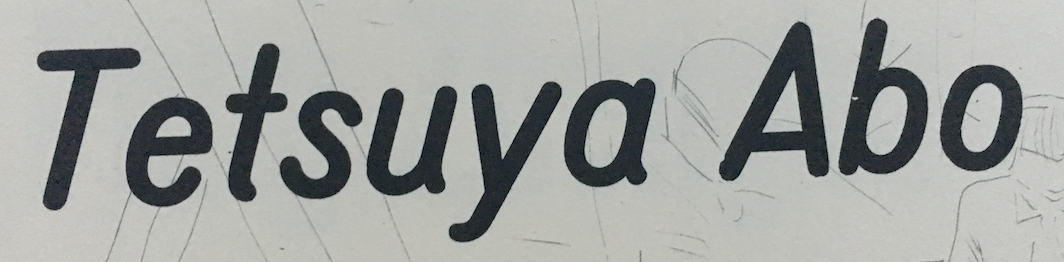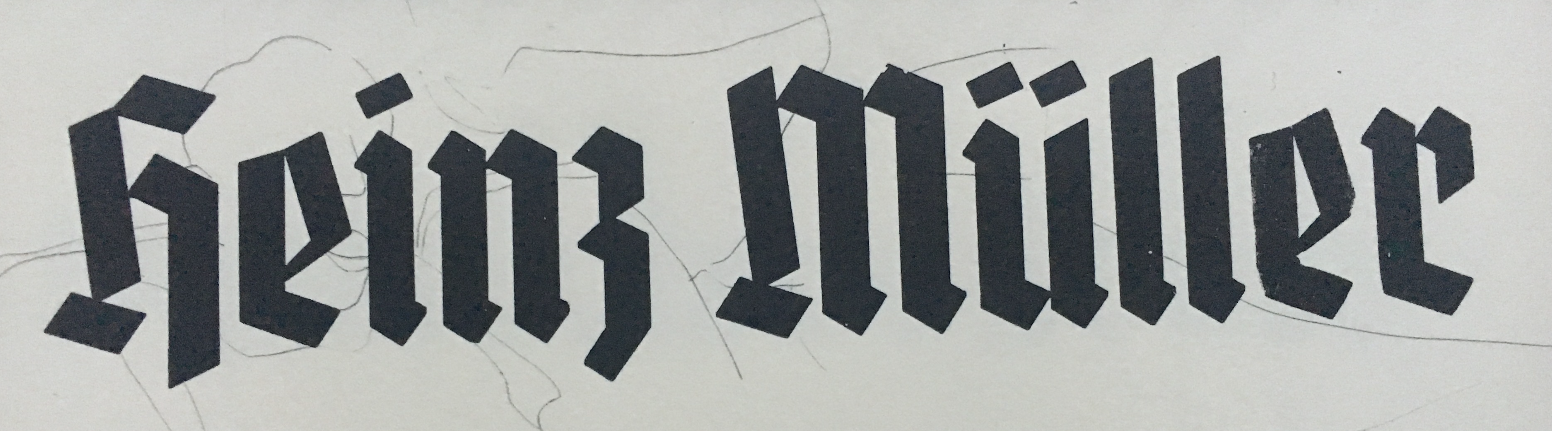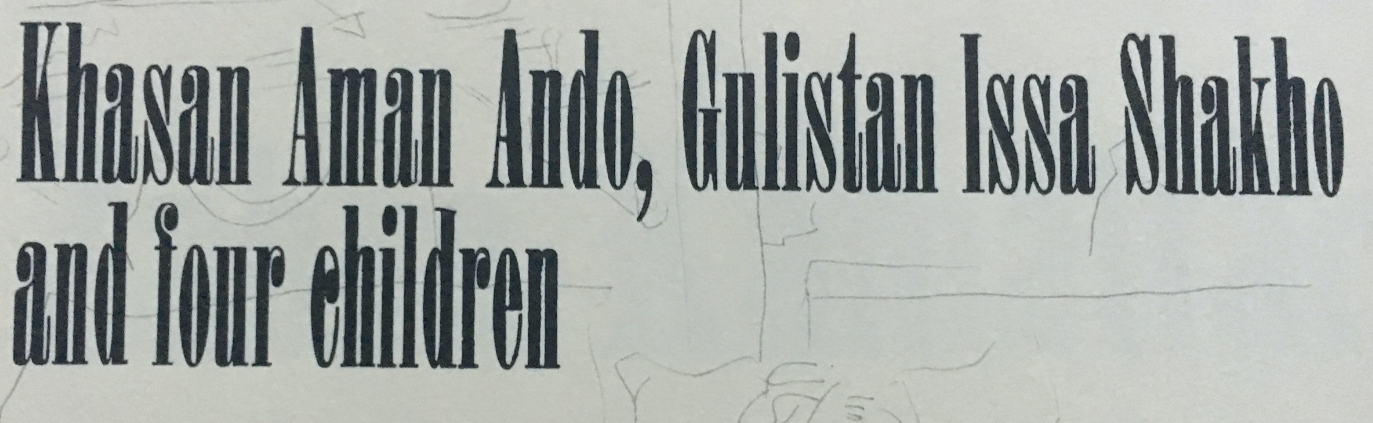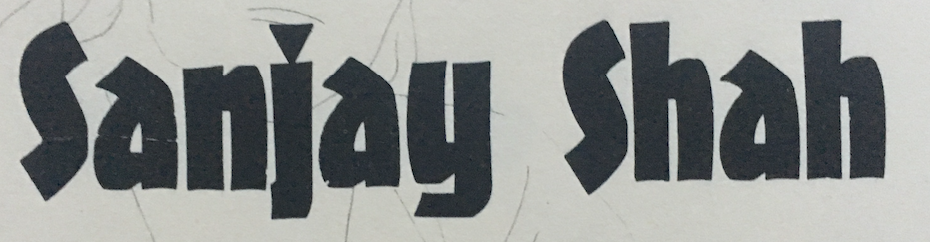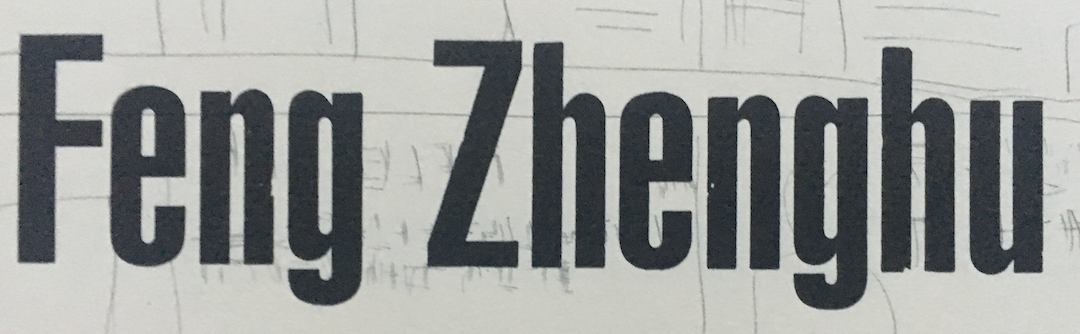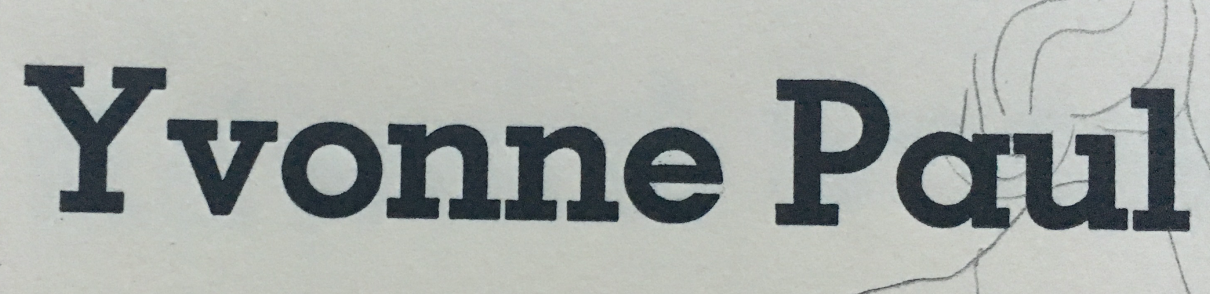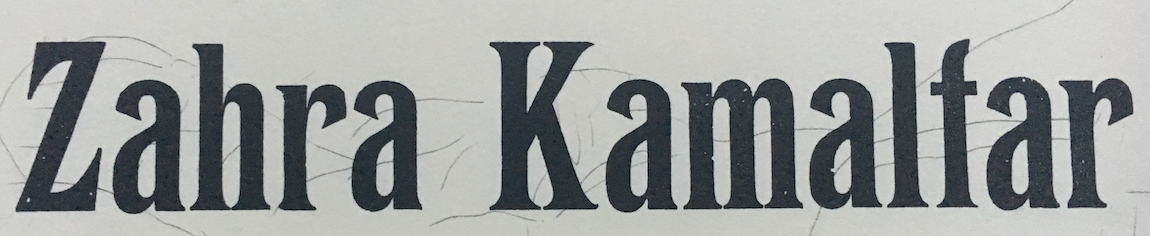
Suche Hilfe bei Identifizierung von Bleisatz-Schriften aus Hersbrucker Bücherwerkstätte
ich habe letzte Woche in der Hersbrucker Bücherwerkstätte http://www.hersbrucker-buecherwerkstaette.de/ ein kleines Heft gedruckt, und nun bin ich dabei die von mir verwendeten Schriften zu recherchieren. Es gibt die Hersbrucker Bücherwerkstatt seit fast 50 Jahren und die Betreiber – gelernte Drucker – haben einige Schriften vor dem Müll gerettet. Die Schrift-Schubladen sind  allerdings sind nicht beschriftet und es wurde auch nicht archiviert, woher die Schriften stammen.
Einige Schiften konnte ich identifizieren, bei anderen bin ich total ratlos. Alles, was ich bisher rausgefunden habe schreibe ich auch unter die Bilder. Ich bin daran interessiert mehr über diese Schriften herauszufinden und ich lade hier ein paar Fotos meines Druckergebnisses hoch, die die Schriften zeigen. Kurz zur Erläuterung der Schriftbeispiele: ich habe 12 Namen in 12 unterschiedlichen Schriften gesetzt und geduckt. Es handelt sich um Personen, die mehr als eine Woche auf Flughäfen gelebt haben. Gründe dafür sind meist Protest, Asylsuche oder Probleme beim Reise / im Urlaub (künstlerisches Projekt).
Yvonne Paul
Beschriftung der Schublade: Memphis
Die Memphis von Rudolf Wolf erschien ab 1929 bei der D. Stempel AG. Die Schrift kombinierte die geometrischen Konstruktionsprinzipien, die Ende der 1920er Jahre populäre geworden waren, mit den zu dieser Zeit ebenfalls beliebten Eqyptienne-Schriften im Stile des 19ten Jahrhunderts. als eine Art „Futura mit Slab-Serifen“ wurde die Memphis rasch zu den beliebtesten Schriften hier Art. Digitalisierungen gibt es z. B. von Linotype und URW +++
Mohammed al Bachish
Keine Beschriftung der Schublade
Heinz Müller
Beschriftung der Schublade: Fette Deutschland
Denis Luis de Souza
Beschriftung der Schublade: Berliner Grotesk
1913 von H. Berthold AG als Teil der „Block Serie in der Akzidenz“ veröffentlicht. Gestaltet eventuell von Oppenheim.
1973 überarbeitete Erik Spiekermann die Schrift und ergänzte sie mit einem Bold Schnitt.
Sanjay Shah
Keine Beschriftung der Schublade
258704388_Bildschirmfoto2018-06-09um20_54_42.png.61ad06ed2c5378b47f01efb5c8cdb599.pngEdward Snowden
Keine Beschriftung der Schublade
Khasan Aman Ando, Guisan Issa Shakho and four children
Keine Beschriftung der Schublade
Tetsuya Abo
Beschriftung der Schublade: Norm-Cursiv
(Konnte dadurch aber leider bisher auf keine Fährte kommen)
647996735_Bildschirmfoto2018-06-09um20_54_19.png.2100dc910db896a9125ab66cc208472c.pngZarah Kamalfar
Keine Beschriftung der Schublade369862981_Bildschirmfoto2018-06-09um20_53_44.png.295e8fa81221ee69ec0648c35a23564e.png
Feng Zhenghu
Sieht aus wie die Swiss 924 von Bitstream. https://www.linotype.com/de/1086602/swiss-924-regular-product.html
Ich vermute, dass das Original Schift Design auf die Hanseatic von Stempel (1890) zurückzuführen ist.
Mehran Karimi Nasseri
Beschriftung der Schublade: Schwabacher
Habe die richtige Schrift als Freefont gefunden: https://www.1001freefonts.com/yonkers.font
Mich würde hier aber die genauere Geschichte interessieren. https://de.wikipedia.org/wiki/Schwabacher
Hassan Al Kontar
Beschriftung der Schublade: Ctc. (oder Clc. ?) Antiqua Halbfett
Tetsuya Abo
Beschriftung der Schublade: Norm-Cursiv
(Konnte dadurch aber leider bisher auf keine Fährte kommen)
Die würde ich mal als DIN 16 einsortieren, also die "Normschrift" mit der ich in den 1970er Jahren mein Berichtsheft führen musste.
Digital bei nit: http://www.peter-wiegel.de/TGL_0-16.html
Die Schwabacher habe ich auch digitalisiert, ich hatte sie  in einem Seemann-Nachtrag als Hamburger Schwabacher gefunden.
Khasan Aman Ando, Guisan Issa Shakho and four children => Onyx ... aber welche?
Typeface:    Onyx
Designer:    Gerry Powell
Year:        1937
Die läuft aber etwas zu weit. Es gibt auch eine recht ähnliche Bodoni Poster Compressed von Monotype, aber auch diese läuft zu weit. Nach meinem Bauchgefühl ist das eine typische extraenge Retro-Klassiszistische-Antiqua aus den (späten) 1930ern. Die extraengen Retros aus der Zeit um die Jahrhundertwende 1900 waren etwas näher an den Werken von Bodoni. Wühle Dich einfach mal durch die ähnlichen Schriften zur Arsis und Onyx und schau Dir die Angaben dazu an. Damit solltest Du in etwa ein Gefühl für das Umfeld bekommen.